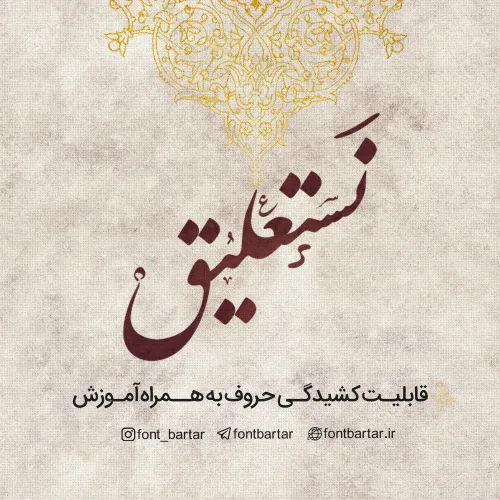
فونت فارسی نستعلیق علما
فونت نستعلیق علما ، برای شما عزیزان و همراهان گرامی آماده شده است که ساختار پیچیده ای دارد و به همین واسطه در دسته فونت های گرافیکی پیچیده قرار می گیرد،طراحی این فونت توسط مصطفی العباثیری انجام شده است و فونت جدید ۲۰18 است، فونت فارسی نستعلیق علما را میتوان برای طرح های گرافیکی ، تایپوگرافی ، طراحی لوگو استفاده نمود هم چنین این فونت برای استفاده در عناوین نیز مناسب می باشد،هم اکنون این فونت زیبا و کاربردی را می توانید از فونت برتر بصورت رایگان دریافت نمایید.
فونت فارسی نستعلیق علما مورد استفاده برای:
• طراحان وب سایت و گرافیست های خلاق می توانند از این مجموعه زیبا فونت در طراحی پروژه های تبلیغاتی و تجاری خود کمک بگیرند.